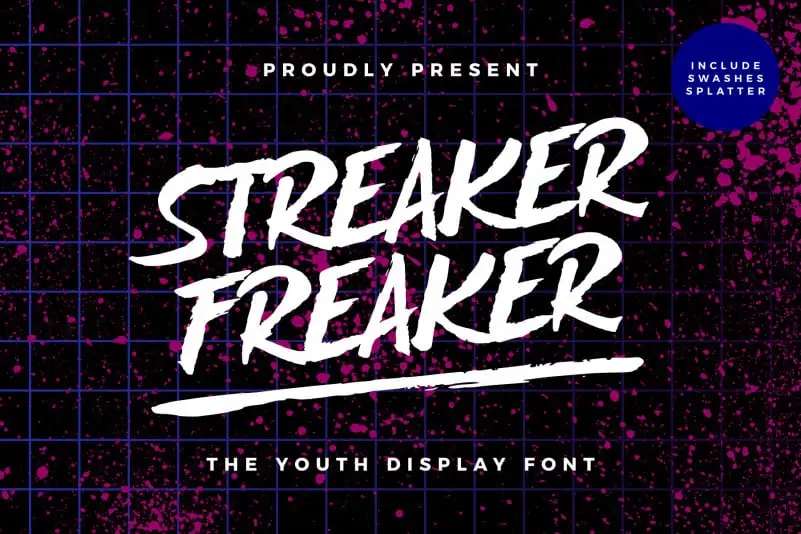
Esta é uma fonte brush expressiva que pode ser usada em qualquer tipo de projeto comercial. Ideal para criar sensações jovias e entusiasmadas, ela é perfeita para aplicativos em camisetas, lenços, logotipos, menus, acessórios, promoções de marca e muito mais. A Streaker Font oferece um toque único que certamente dará seu design aquele toque especial e moderno, combinando bem com qualquer estilo. Seja você designer gráfico ou simplesmente alguém que gosta de fazer coisas criativas em casa, essa fonte é uma excelente opção para incrementar seus projetos.